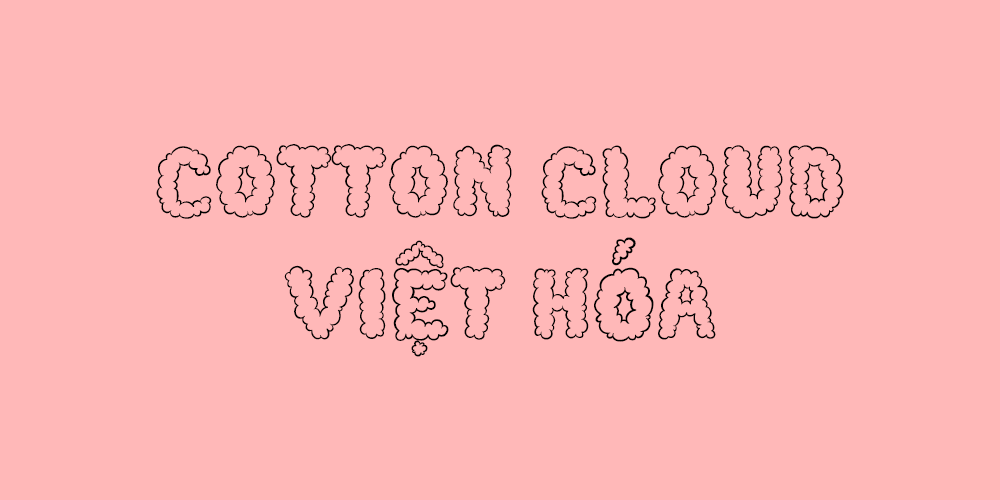
Font 1FTV Cotton Cloud
Nếu bạn đang tìm kiếm một kiểu chữ độc đáo và sáng tạo để làm nổi bật dự án thiết kế của mình, thì Font 1FTV Cotton Cloud là lựa chọn hoàn hảo. Được lấy cảm hứng từ hình ảnh những đám mây bồng bềnh và nhẹ nhàng, font chữ này không chỉ mang lại cảm giác thoải mái mà còn tạo nên nét thẩm mỹ hiện đại và tinh tế. Với các đường nét mềm mại và thiết kế tối giản, Font 1FTV Cotton Cloud phù hợp cho nhiều ứng dụng, từ thiết kế đồ họa, in ấn đến quảng cáo và trang trí nội thất. Khám phá sức hấp dẫn của mẫu font viết tay này để mang đến một làn gió mới cho các dự án của bạn.